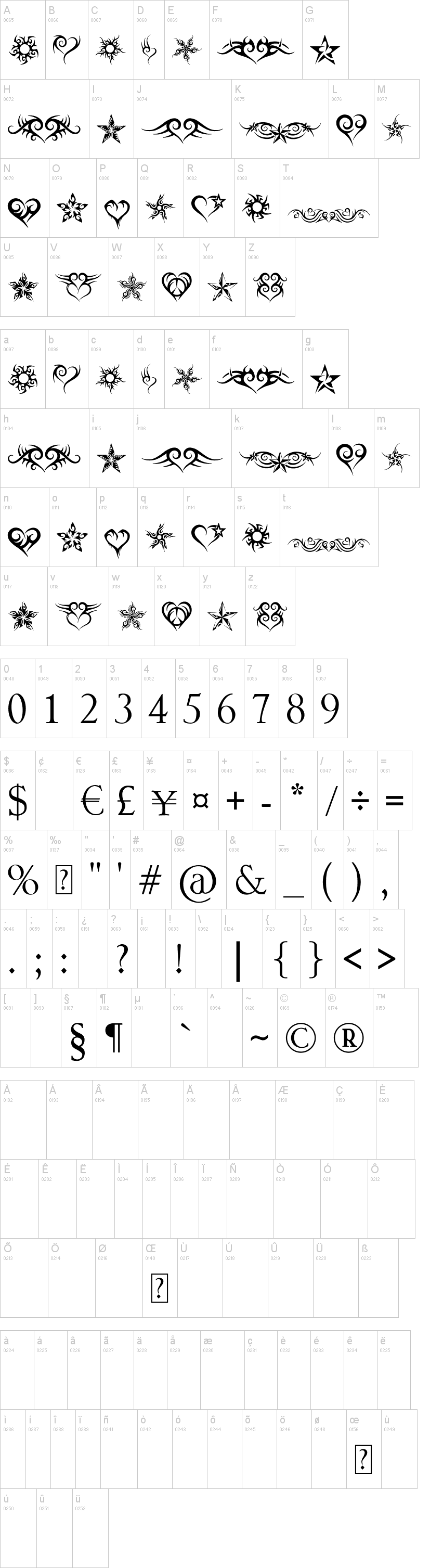
Hearts and Stars 字体是一款非常可爱的英文字体,它由一系列由星星和心形组成的字母组成。它具有温暖、可爱、柔和的特点,可以用来装饰婚礼、生日聚会、儿童活动等等。它有着漂亮的、柔和的轮廓,可以提供视觉上的美感。Hearts and Stars 字体可以帮助你建立一个美好的氛围,让你的照片、文字和设计更加有趣可爱。内容介绍
Hearts and Stars是一款非常不错的手写艺术字体,具有很好的视觉感,适合于文化类的宣传设计、商业类品牌的广告和产品包装设计以及个性化文字排版等较多场景。